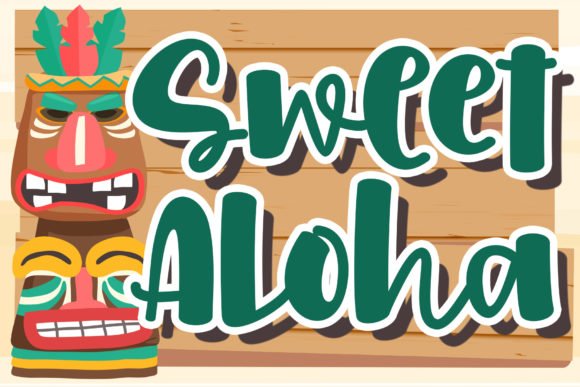
Sweet Aloha - это веселый, причудливый и уникальный по форме рукописный шрифт.
Если вы используете его для дизайна, связанного с мультфильмами, детскими играми или просто для любого творчества, требующего милого прикосновения, этот шрифт станет отличным выбором.